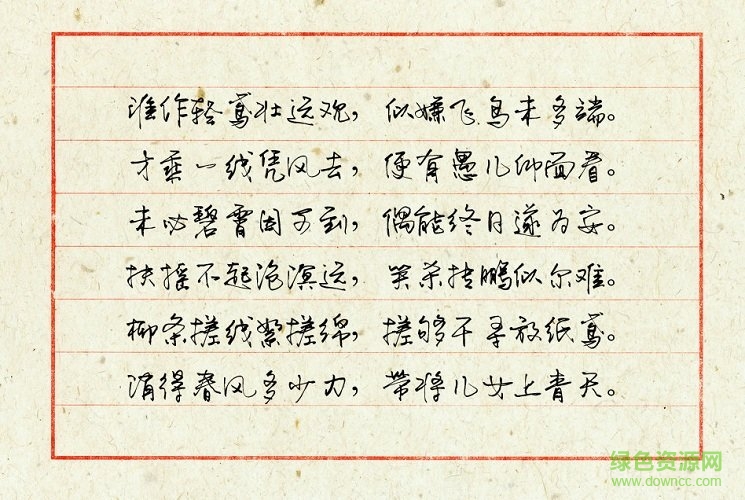
默陌紙鳶行草書是一款字跡連貫狂放的行草字體,集合了行書和草書的特點,給你狷介而秀氣、放浪而不羈的韻味,來綠色資源網(wǎng)嘗試一下吧!
默陌紙鳶行草書是一款行草硬筆手寫風格的字體,比之默陌信箋手寫體,連筆流連貫穿,使得筆畫更加流暢恣意,氣韻更加舒展瀟灑,字體中宮更大,筆畫更粗,增強了字體辨識度,提高了實用性。
默陌紙鳶行草書是一款有著潦草而不凌亂的藝術字體,體驗紙鳶肆意飛揚的灑脫和自由,字跡清秀而柔和,適用于海報設計、廣告創(chuàng)意、平面設計等多種場合。